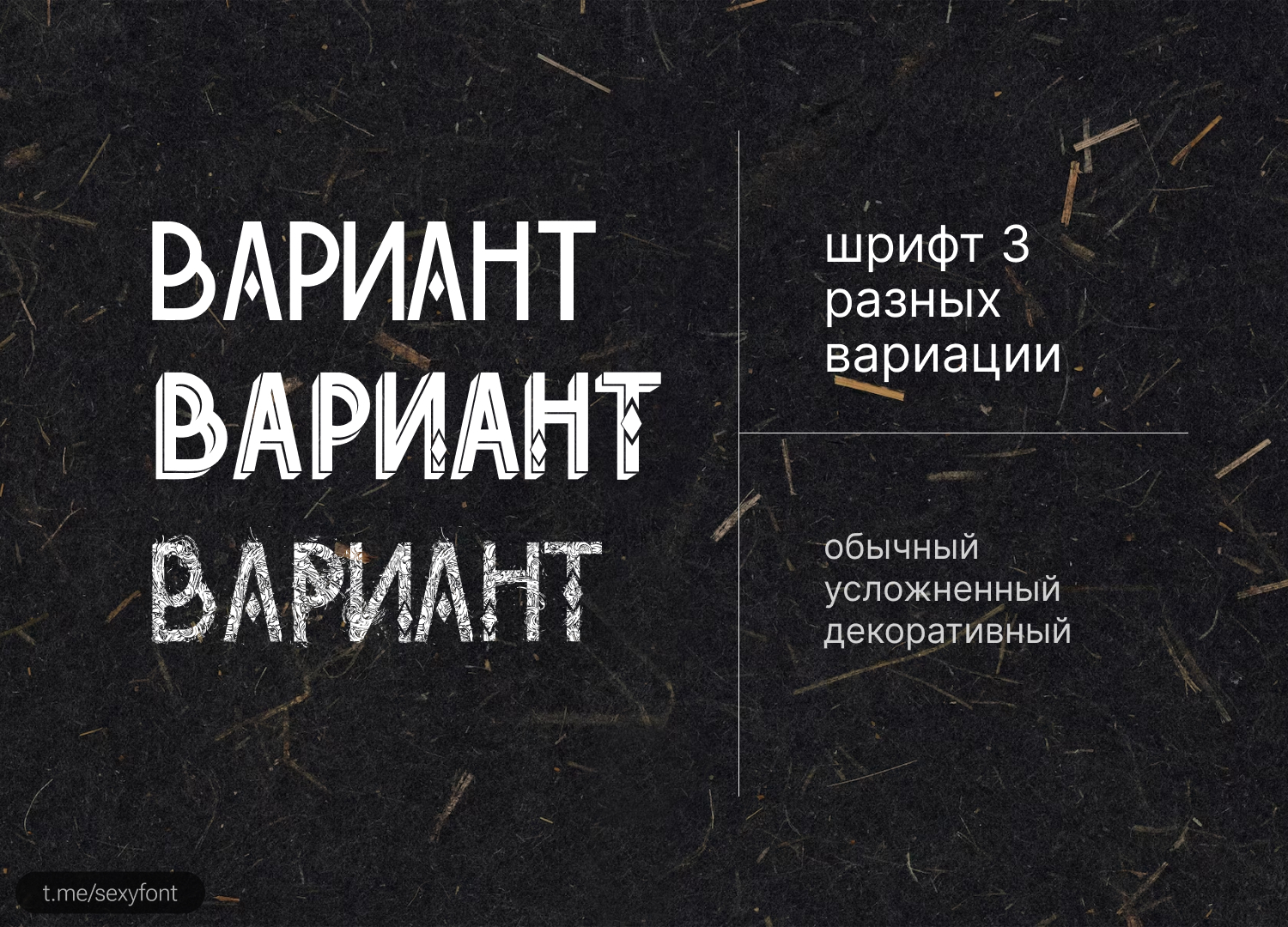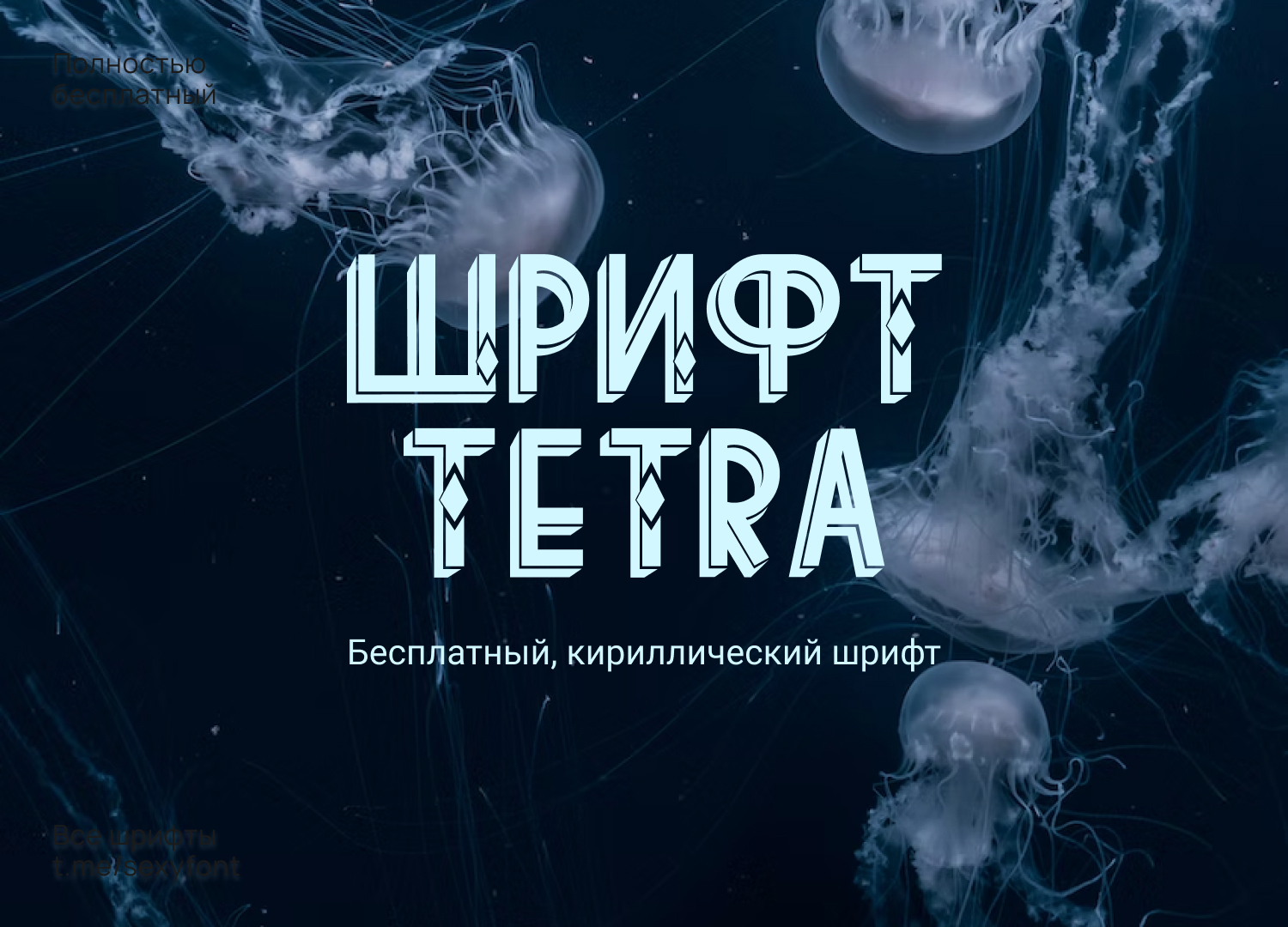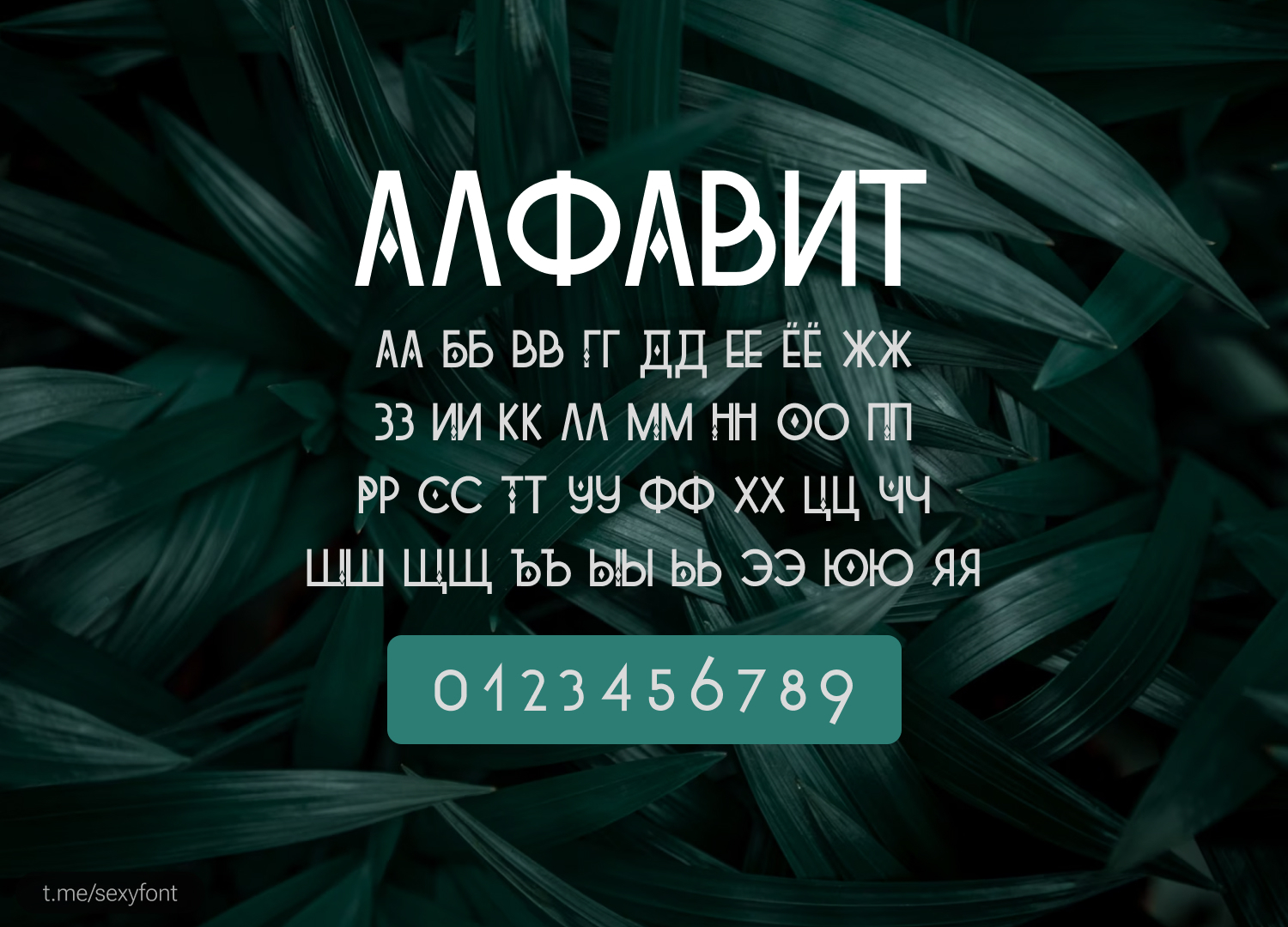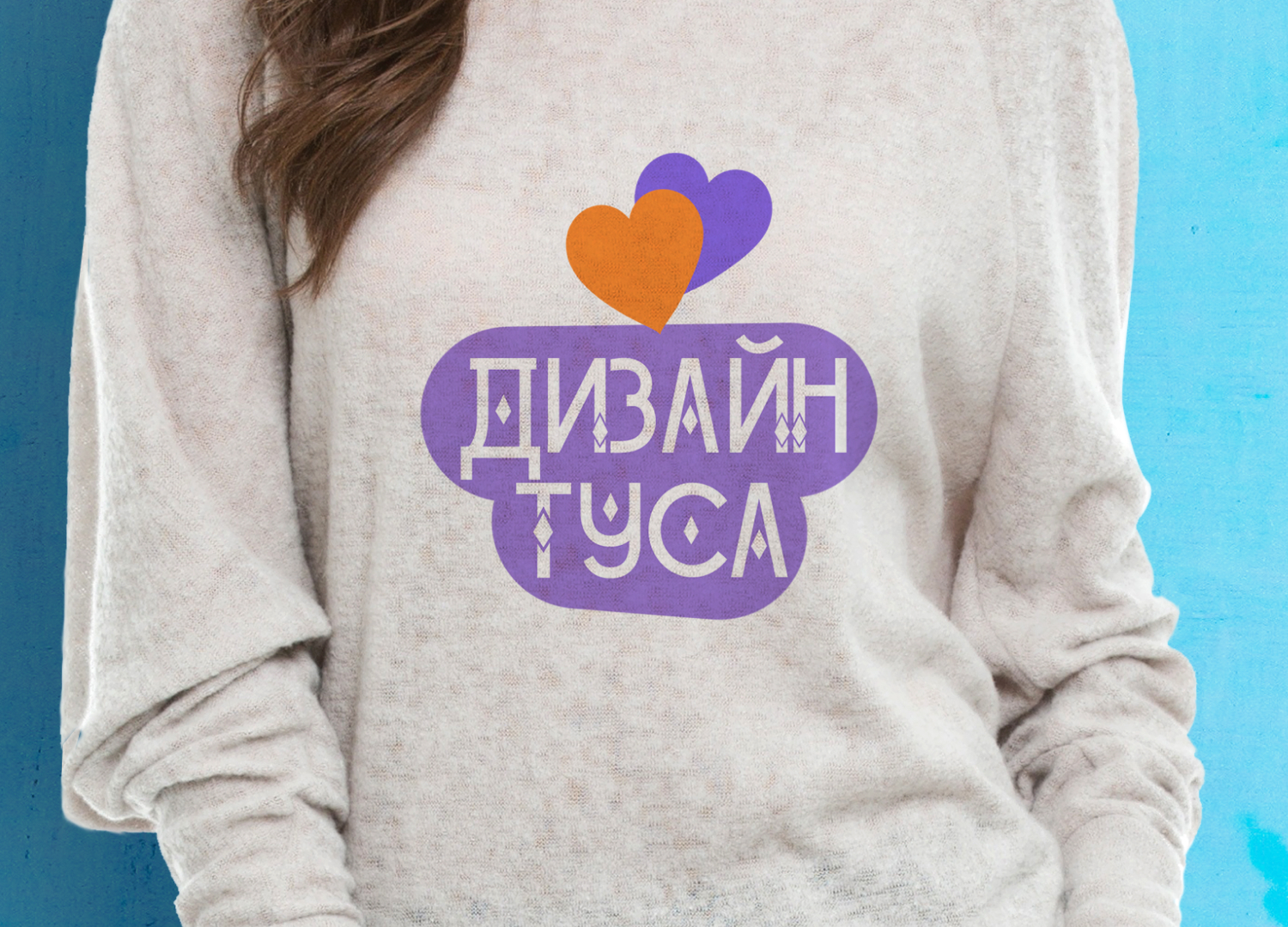
Шрифт тетра. Кириллица
Tetra. Необычный кириллический шрифт. По сути это 2 шрифта: Тетра и тетра декоративный. Оба по-разному выглядит в зависимости от строчных или прописных букв. Лайкос автору за старания. Шрифт полностью бесплатный для личного и коммерции. Автор: Alex Frukta